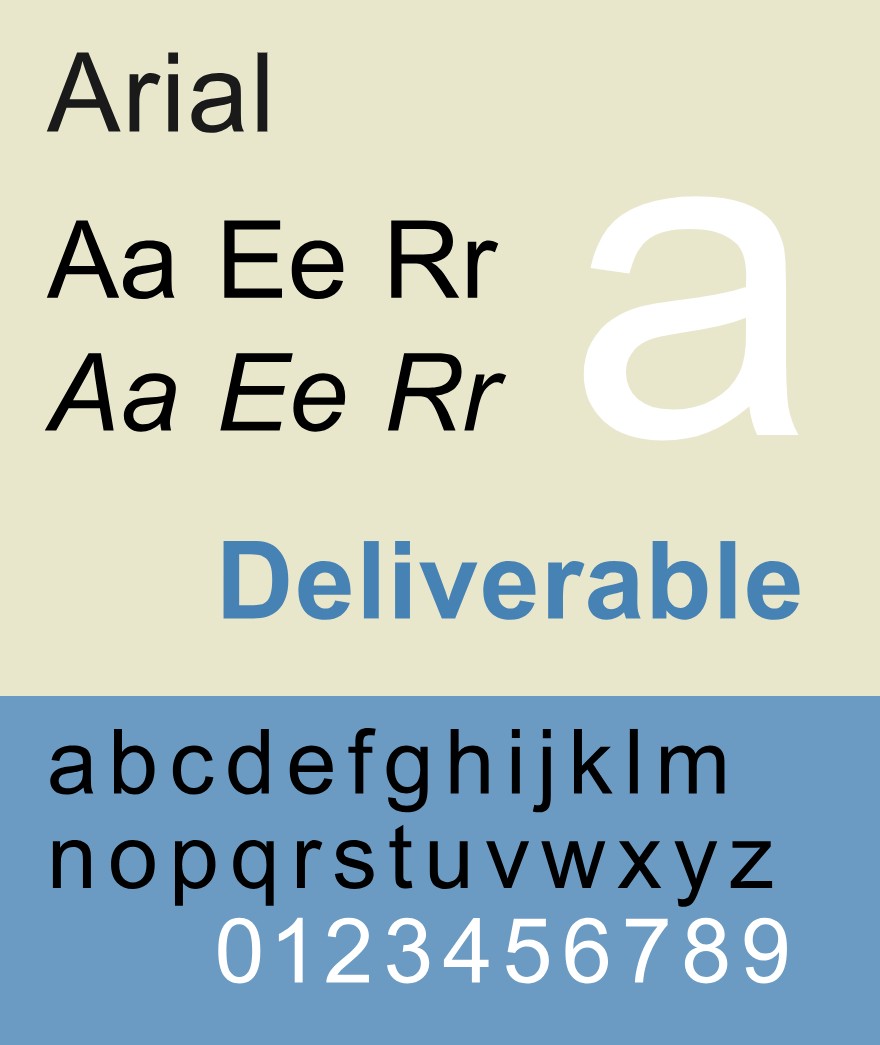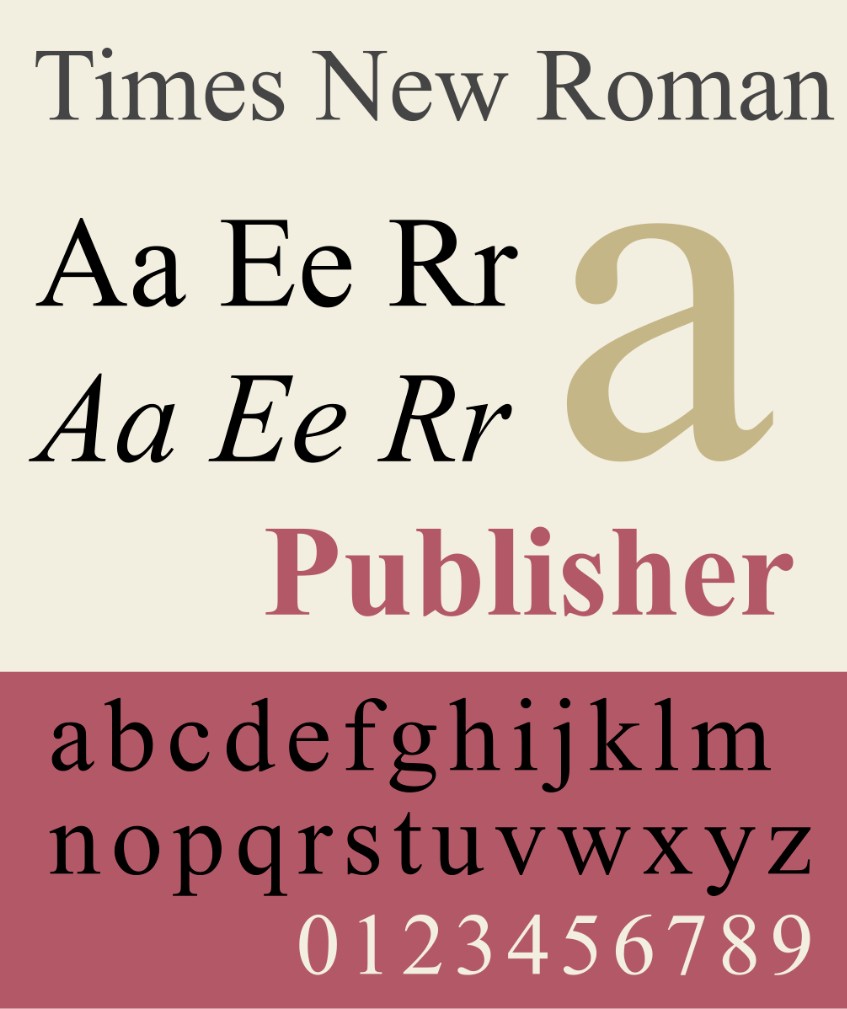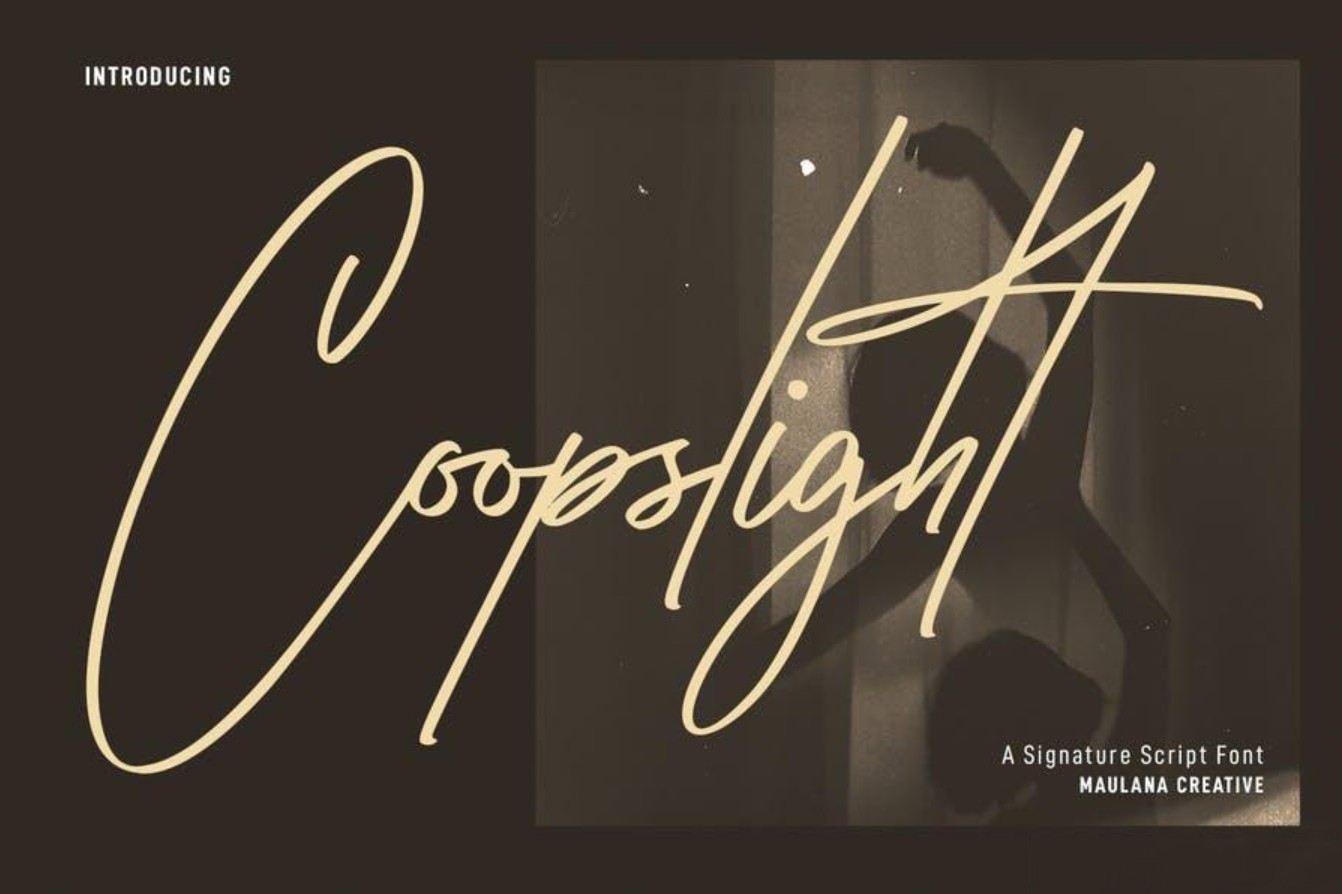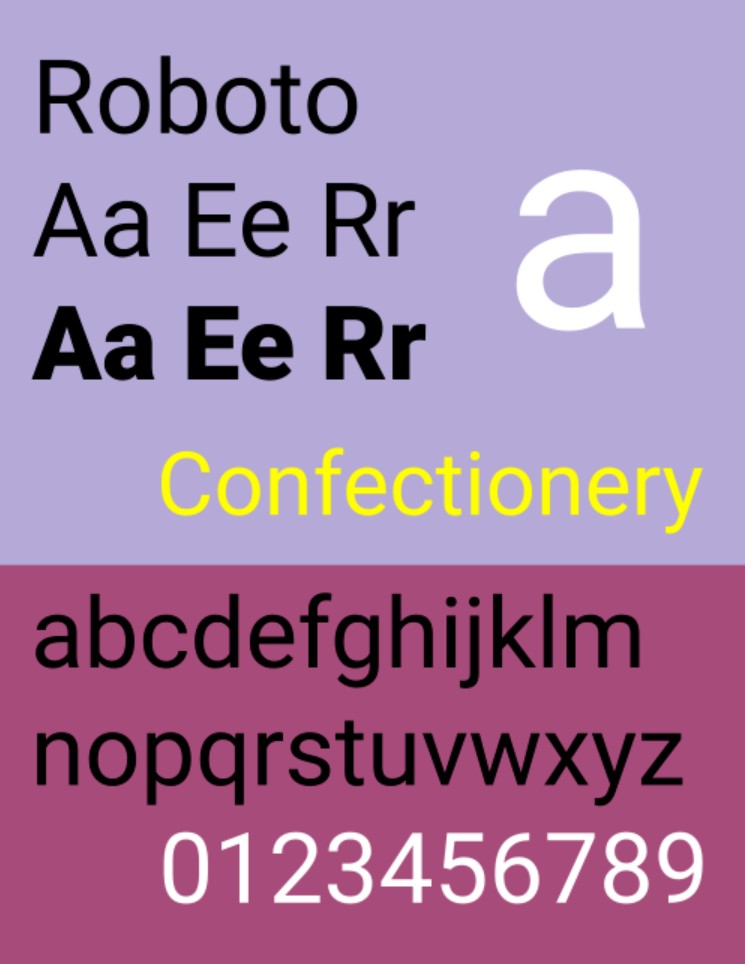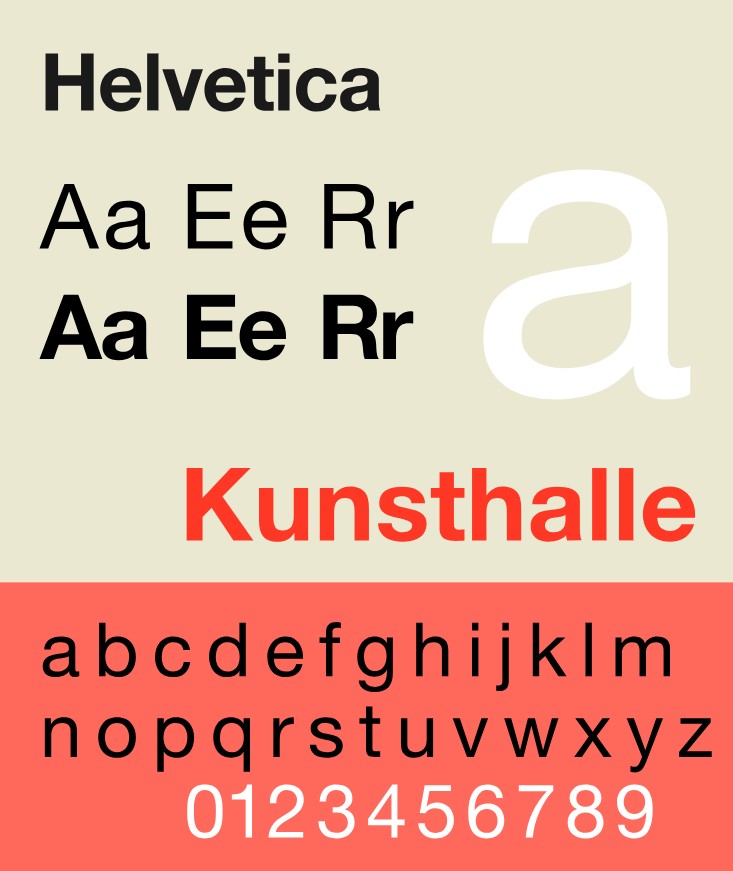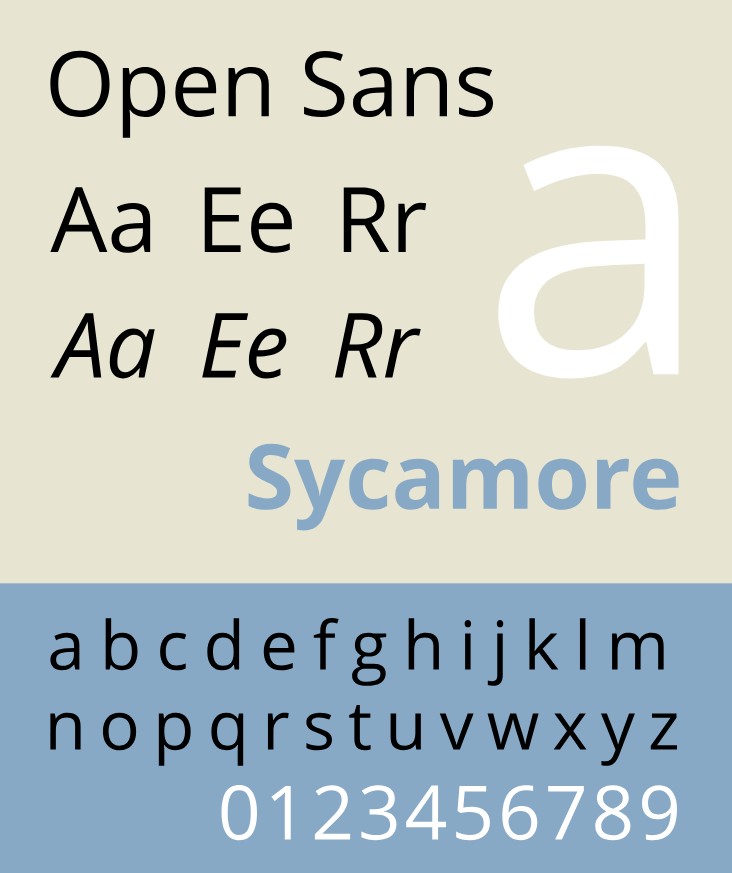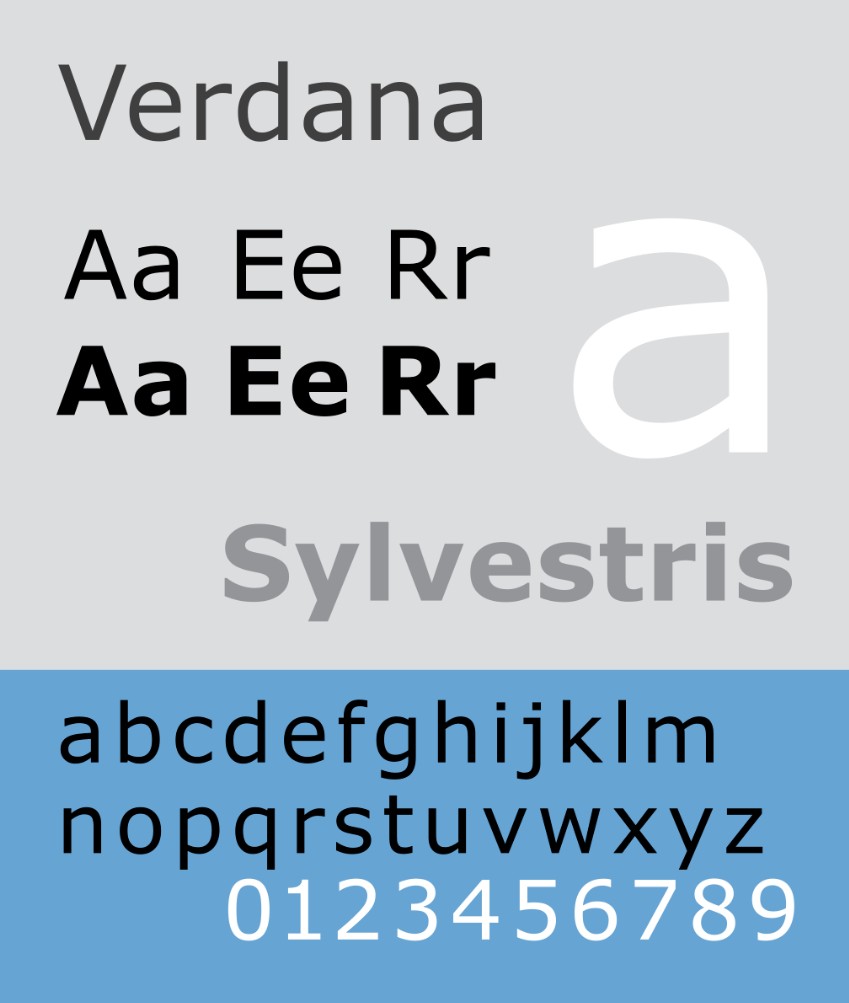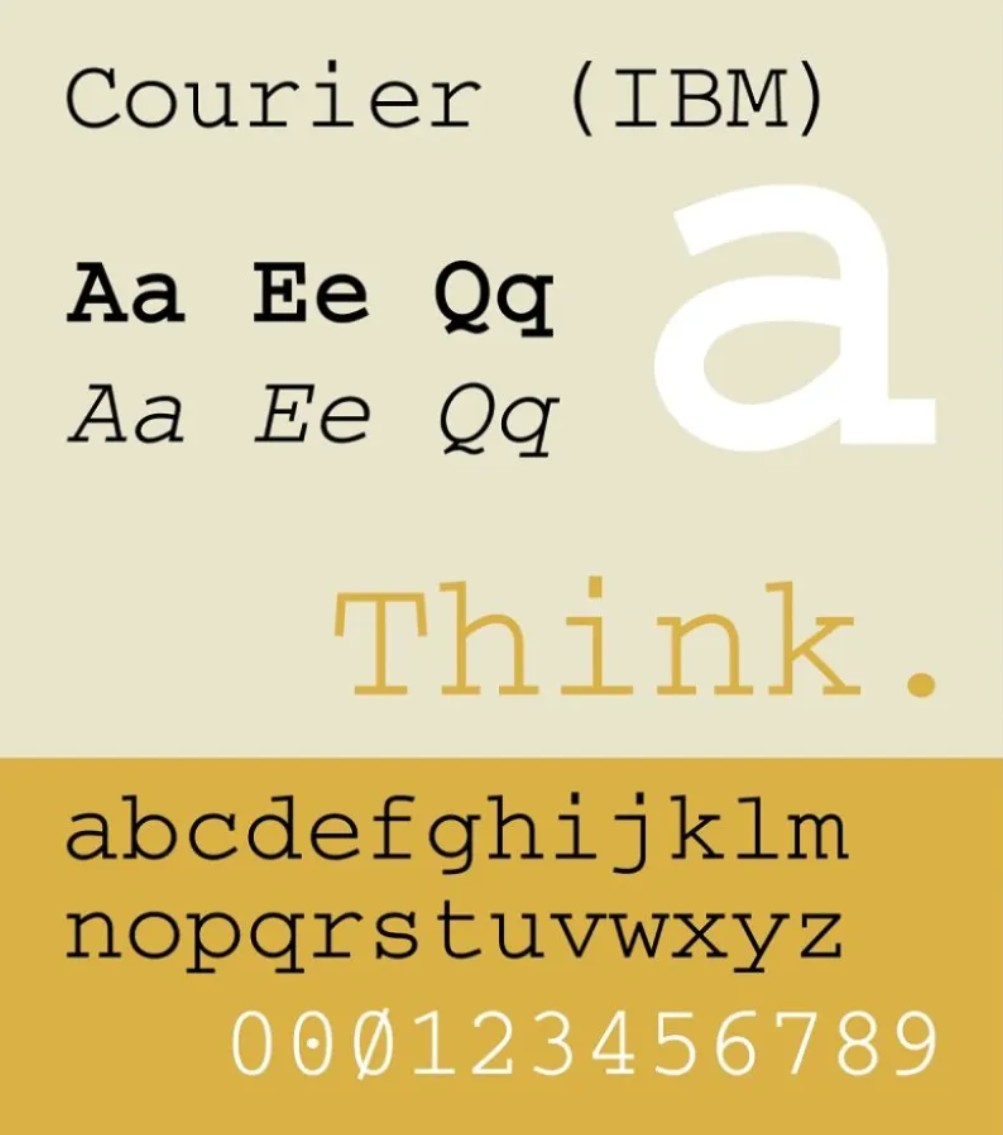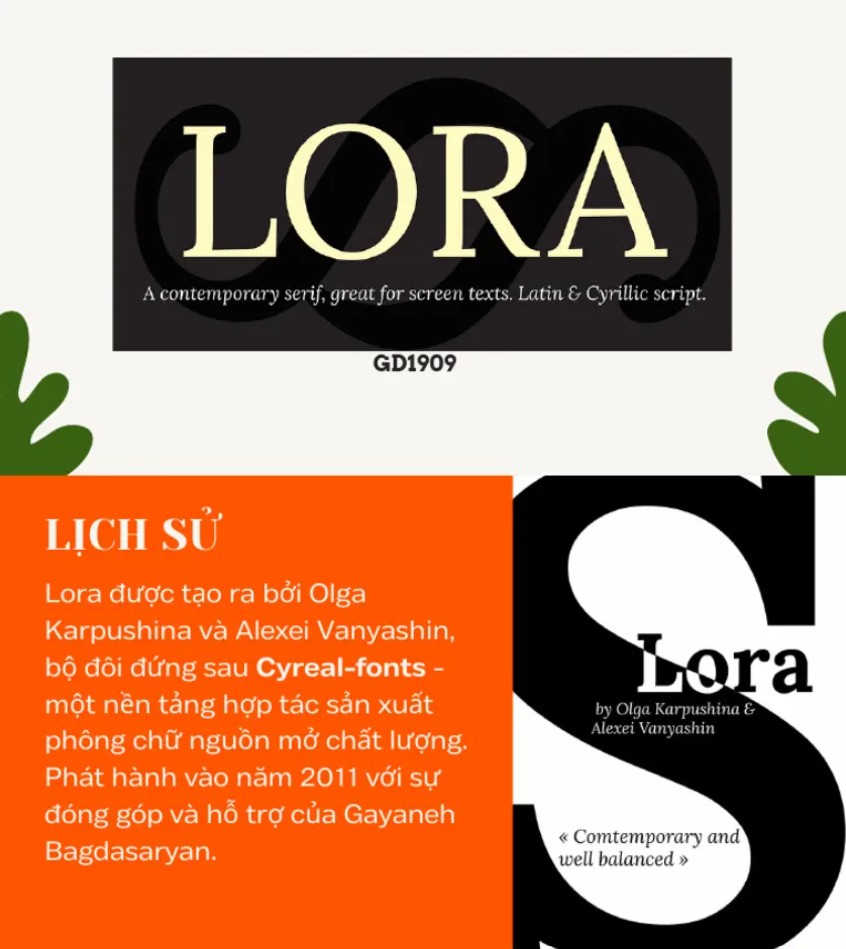
Font chữ đẹp tiếng Việt: Xu hướng thiết kế 2025 bạn không thể bỏ qua
Tìm hiểu các font chữ vừa đẹp vừa tối ưu cho tiếng Việt, giúp nâng tầm thẩm mỹ dự án của bạn. Xu hướng năm 2025 tập trung vào sự tối giản, hiện đại và dễ đọc.
Bước vào năm 2025, khi sự tối giản, tính thẩm mỹ và trải nghiệm người dùng được đặt lên hàng đầu, nhu cầu tìm kiếm những font chữ đẹp tiếng Việt ngày càng tăng mạnh. Điểm đặc biệt trong thiết kế dành cho thị trường Việt Nam nằm ở khả năng hỗ trợ đầy đủ dấu tiếng Việt. Không ít font chữ quốc tế được yêu thích nhưng lại thiếu tính năng Việt hóa hoàn chỉnh, khiến quá trình sử dụng gặp nhiều hạn chế. Vì vậy, bước sang 2025, xu hướng font chữ không chỉ đẹp mà còn phải thân thiện với tiếng Việt, hỗ trợ đầy đủ bộ ký tự, độ đậm nhạt phong phú và đặc biệt là tính ứng dụng cao trong cả thiết kế thương hiệu, sản phẩm in ấn, giao diện web lẫn nội dung mạng xã hội. Bài viết này sẽ giúp bạn hiểu rõ hơn về lợi ích của việc sử dụng font chữ đẹp, cập nhật top font chữ đẹp tiếng Việt được ưa chuộng nhất năm 2025 và gợi ý những mẹo quan trọng để bạn kết hợp font một cách hài hòa, chuyên nghiệp.
1. Font chữ đẹp có lợi ích như thế nào?
Font chữ tác động trực tiếp đến cách người xem cảm nhận nội dung, nhưng nhiều người lại thường xem nhẹ tầm quan trọng của nó. Trong thực tế, font chữ có khả năng định hình trải nghiệm thị giác, ảnh hưởng đến khả năng đọc, cảm xúc và thậm chí là mức độ tin cậy mà người xem dành cho sản phẩm.
Lợi ích đầu tiên của font chữ đẹp nằm ở khả năng truyền tải thông điệp rõ ràng và hiệu quả. Một font chữ dễ đọc giúp người xem tiếp nhận thông tin nhanh chóng hơn, không bị phân tâm bởi những đường nét quá phức tạp hay thiếu cân đối. Điều này đặc biệt quan trọng trong thiết kế in ấn như brochure, catalogue, poster, hoặc trong môi trường digital như website và ứng dụng. Các loại font serif truyền thống mang đến cảm giác trang trọng và tin cậy, trong khi font sans serif hiện đại lại đem đến sự tối giản, thân thiện và dễ tiếp cận.
Lợi ích thứ hai là yếu tố thẩm mỹ. Font chữ chính là “giao diện” của nội dung và một thiết kế đẹp luôn bắt đầu từ sự hài hòa trong kiểu chữ. Khi bạn chọn đúng font, mọi yếu tố còn lại như màu sắc, bố cục, hình ảnh đều trở nên cân đối và chuyên nghiệp hơn. Ngược lại, nếu font chữ lựa chọn sai, sản phẩm dù được đầu tư kỹ về hình ảnh cũng mất đi sự tinh tế cần thiết.
Một lợi ích quan trọng khác của font chữ đẹp là khả năng xây dựng nhận diện thương hiệu. Người xem có thể quên hình ảnh hay câu slogan, nhưng lại nhớ rất rõ cảm giác mà kiểu chữ mang lại. Những thương hiệu lớn như Google, Spotify hay Airbnb đều sở hữu bộ font đặc trưng nhằm tăng tính nhận diện. Với các doanh nghiệp Việt Nam, việc chọn font hỗ trợ tiếng Việt đẹp mắt và nhất quán sẽ giúp thương hiệu thể hiện được bản sắc riêng trên mọi nền tảng truyền thông.
2. Font chữ đẹp được ưa chuộng nhất 2025
Xu hướng font chữ 2025 tại Việt Nam có sự kết hợp giữa truyền thống và hiện đại. Các font serif mang tính cổ điển quay trở lại mạnh mẽ, trong khi nhóm sans serif hiện đại vẫn giữ vị trí hàng đầu nhờ tính ứng dụng cao. Dưới đây là những font chữ vừa đẹp, vừa hỗ trợ tốt tiếng Việt và được sử dụng rộng rãi nhất trong thiết kế năm 2025.
2.1. Times New Roman
Times New Roman là font serif kinh điển, luôn nằm trong danh sách font được sử dụng nhiều nhất trên toàn thế giới. Dù đã xuất hiện từ rất lâu nhưng bước sang 2025, nó vẫn được ưa chuộng nhờ tính trang trọng, dễ đọc và sự cân đối trong từng đường nét. Đây là font thường gặp trong các tài liệu học thuật, báo chí, báo cáo, văn bản hành chính hay sách in. Người dùng Việt Nam quen thuộc với Times New Roman không chỉ vì tính truyền thống mà còn vì font này hỗ trợ đầy đủ dấu tiếng Việt.
Trong thiết kế, Times New Roman phù hợp cho những dự án cần sự tin cậy như ấn phẩm giáo dục, văn phòng, tài liệu nghiên cứu hoặc thương hiệu mang phong cách cổ điển. Khi sử dụng với kích cỡ lớn, font này mang đến cảm giác sang trọng, tinh tường và rất phù hợp cho các tiêu đề nghiêm túc.
2.2. Arial
Arial là font sans serif phổ biến và được xem là lựa chọn “an toàn” trong mọi trường hợp. Với đường nét sạch sẽ, đơn giản, Arial phù hợp cho đa dạng thiết kế từ poster, infographic đến giao diện website. Trong năm 2025, Arial tiếp tục được ưa chuộng bởi khả năng hiển thị tốt trên mọi kích thước màn hình, đảm bảo tính dễ đọc ngay cả khi thu nhỏ.
Một lý do khiến Arial được nhiều nhà thiết kế tin dùng tại Việt Nam là font này có bộ ký tự tiếng Việt đầy đủ và được tối ưu hóa tốt trên các hệ điều hành phổ biến. Arial mang đến phong cách hiện đại, tối giản, rất phù hợp với xu hướng thiết kế gọn gàng của thời đại số.
2.3. Roboto
Roboto là font chữ được Google phát triển dành riêng cho giao diện Android và các sản phẩm web. Đến 2025, Roboto vẫn nằm trong top font chữ được yêu thích nhất tại Việt Nam bởi sự linh hoạt, độ dễ đọc cao và nhiều trọng lượng khác nhau để nhà thiết kế thoải mái kết hợp.
Roboto có sự cân đối giữa nét cơ học của sans serif truyền thống và sự mềm mại tự nhiên của các font chữ hiện đại. Điều này khiến Roboto phù hợp cho hầu hết mọi sản phẩm thiết kế, từ app, website đến ấn phẩm marketing. Hỗ trợ tiếng Việt tốt cũng là điểm cộng lớn giúp Roboto đứng vững ở vị trí top đầu.
2.4. Font Helvetica
Không thể nhắc đến font sans serif mà bỏ qua Helvetica, một trong những font chữ có ảnh hưởng lớn nhất thế kỷ. Helvetica nổi tiếng nhờ sự trung tính, đơn giản và hoàn hảo trong từng chi tiết. Từ các thương hiệu lớn cho đến những chiến dịch quảng cáo toàn cầu, Helvetica luôn là cái tên được lựa chọn.